The Last of Us esta considerado para la gran mayorĂa de expertos de los videojuegos, una de las grandes obras maestras de toda la historia. The Last of Us es un videojuego, que digo uno, es el videojuego jejeje de acciĂłn, aventuras y supervivencia. Desarrollado por Naughty Dog (si los creadores tambiĂ©n de la saga "Uncharted") y lanzado por primera vez en junio de 2013 para PlayStation 3, aunque debido a su enorme Ă©xito, al año siguiente se realizo una excelente remasterizaciĂłn para PlayStation 4.
Al sumergirte en The Last of Us asumes el reto del bueno de Joel y de Ellie, de sobrevivir a travĂ©s de los Estados Unidos postapocalĂptico. Os puede decir por propia experiencia, que The Last of Us es uno de esos juegos que te marcan, de los juegos que recuerdas por siempre y son parte de tu vida. Su historia te atrapa y recomiendo jugarlo junto a tu pareja o tu mejor amigo.
A raĂz de que me fascinará este exquisito juego, y como podĂ©is adivinar ijiji, me surgiĂł la famosa pregunta ¿Que tipografĂa usa The Last of Us?
Tanto en la carátula del juego como en toda las aplicaciones de publicidad y marketing de The Last of Us se ve la misma tipografĂa condensada, en caja alta y con una gran altura de x, pero ¿Cual esta tipografĂa? ¿Esta chula verdad?
Puede ser que esta tipografĂa te suene familiar ya que es una de esas voces anĂłnimas que sin saberlo hemos visto en multitud de lugares a lo largo de nuestras vidas. Por ejemplo, ¿como te quedas si te dijo que esta misma tipografĂa ya la podĂamos ver en los años sesenta en la carátula de la mĂtica pelĂcula de western "El bueno, el feo y el malo" de Clint Eastwood? Curioso ¿verdad?
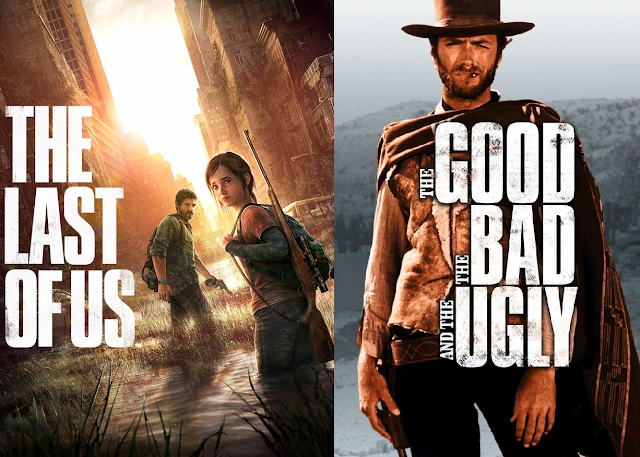
Todo apunta que la tipografĂa en cuestiĂłn es Press Gothic de Aldo Novarese, aunque algunas voces dicen que la tipografĂa de The Last of Us podrĂa ser mas bien Compacta de Fred Lambert. Lo cual cuadrarĂa mas en fechas con la pelĂcula "El bueno, el feo y el malo" ya que este film se estreno por primera vez en 1966 y la tipografĂa Compacta se lanzo en 1963. Mucho mas difĂcil es que Press Gothic sea la tipografĂa empleada en la portada de la pelĂcula de Clint Eastwood, ya que esta tipografĂa vio la luz tres años despues de que la pelĂcula se estrenará.
Y si, es la misma tipografĂa que, como vimos hace poco en Lettering Time, se ha utilizado para el reciente lanzamiento de Tomb Raider 2018, sin duda Compacta esta de moda ;)